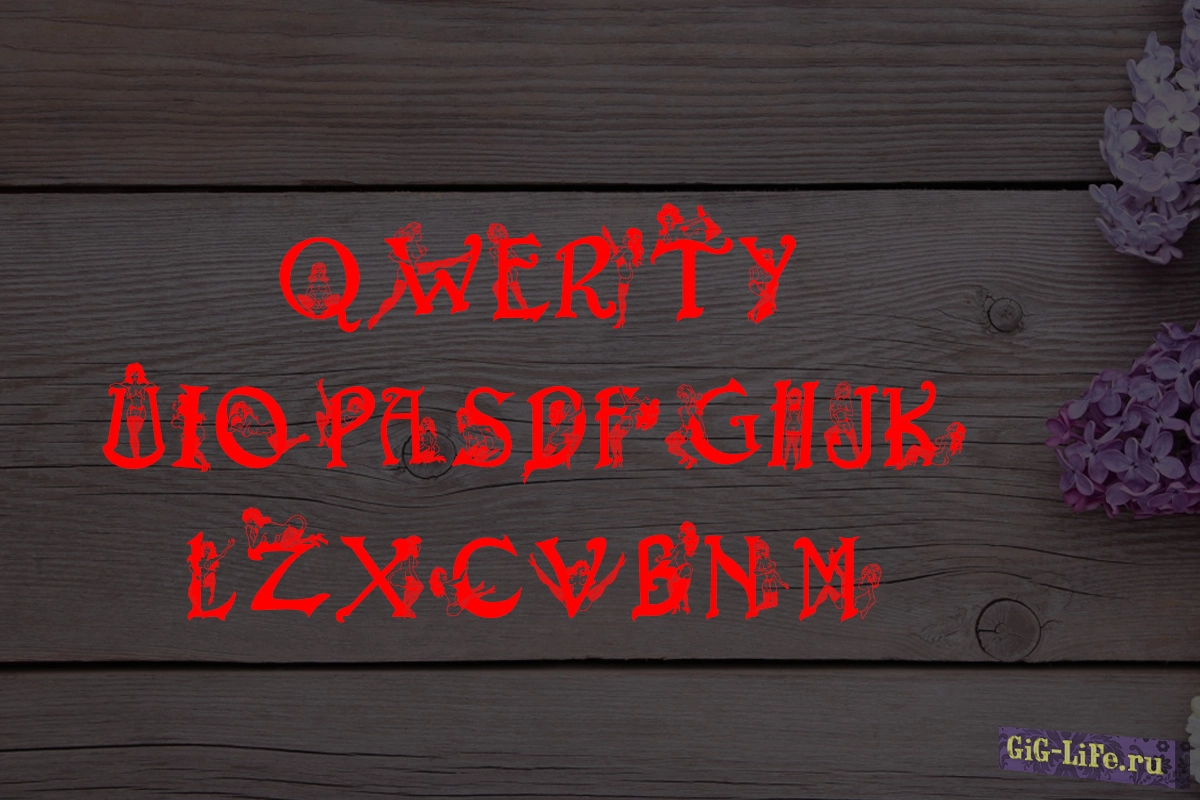
Same-Sex Marriage LDO - это эротический, прописной шрифт, разработанный для использования в Photoshop и других творческих проектах. Он основан на английском начертании.